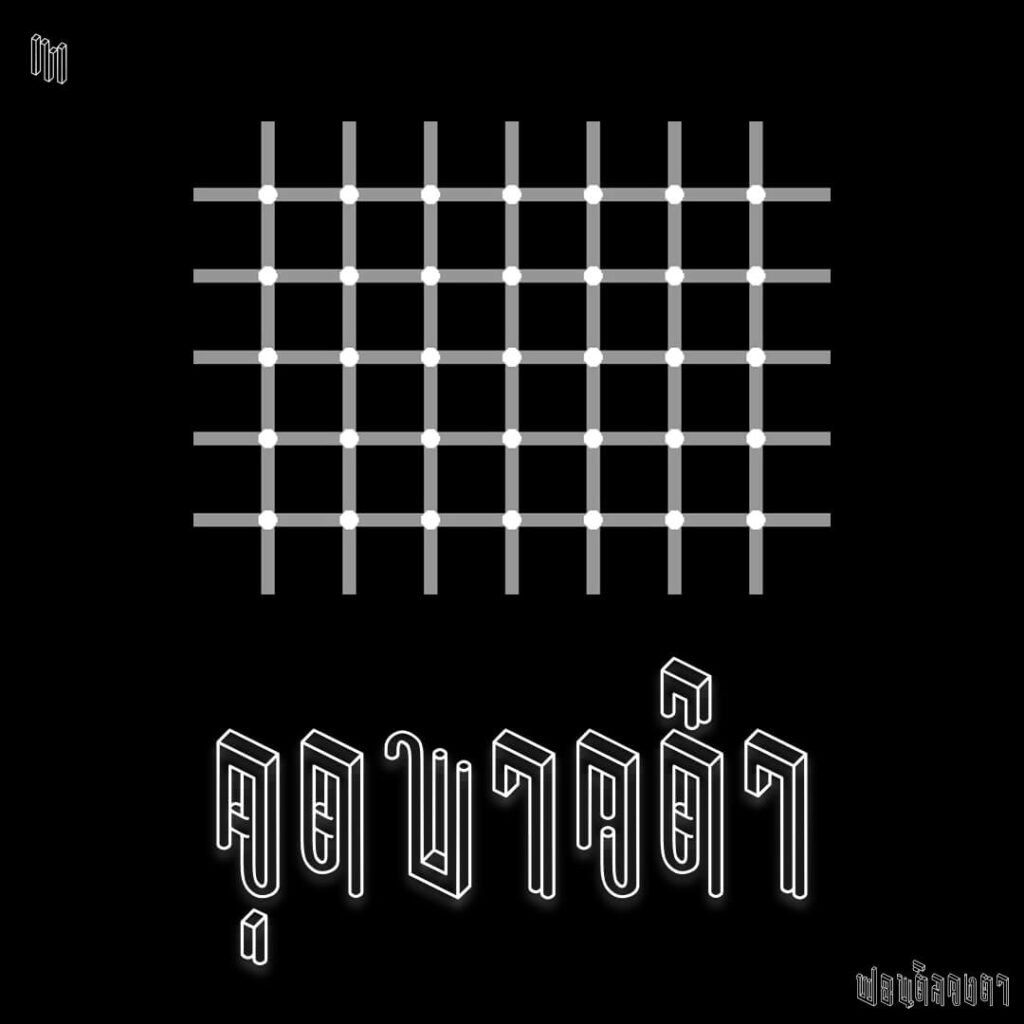
ลวงตา (SOV_LuangTa)
ฟอนต์ลวงตา แนวคิดจาก impossible object illusion ภาพวัตถุที่เป็นไปไม่ได้ (ในโลก 3 มิติ) แต่สมองเราเห็นได้(ไง)… มองผ่านๆ อ่านได้ แต่ถ้าตั้งใจมองจะเอ๊ะ!!
ภาพประกอบเป็น optical illusion ภาพนิ่งแต่วูบวาบเคลื่อนไหวได้